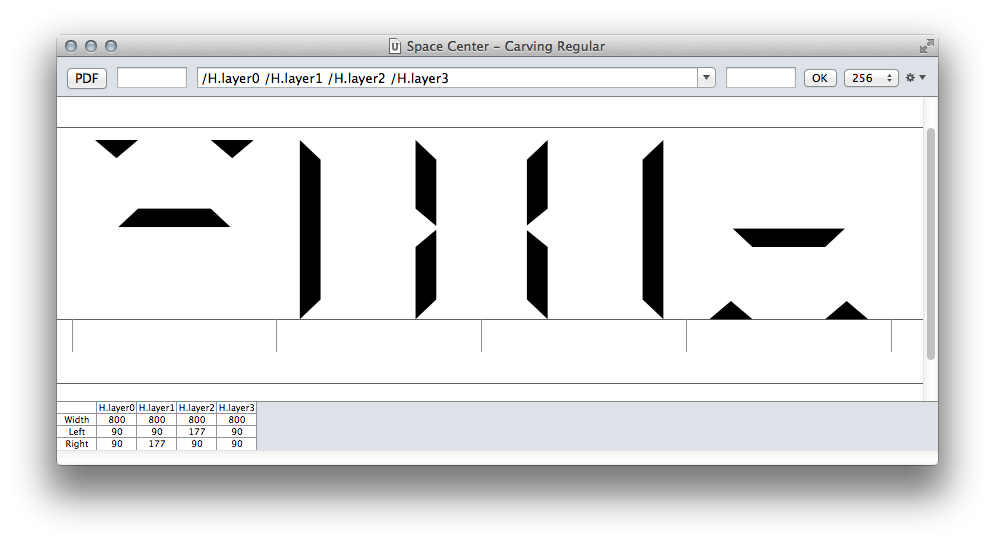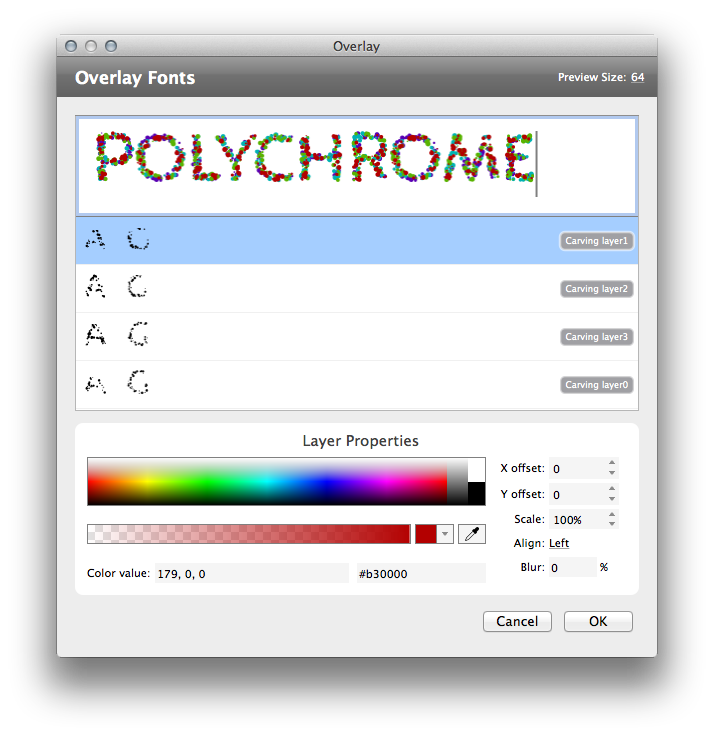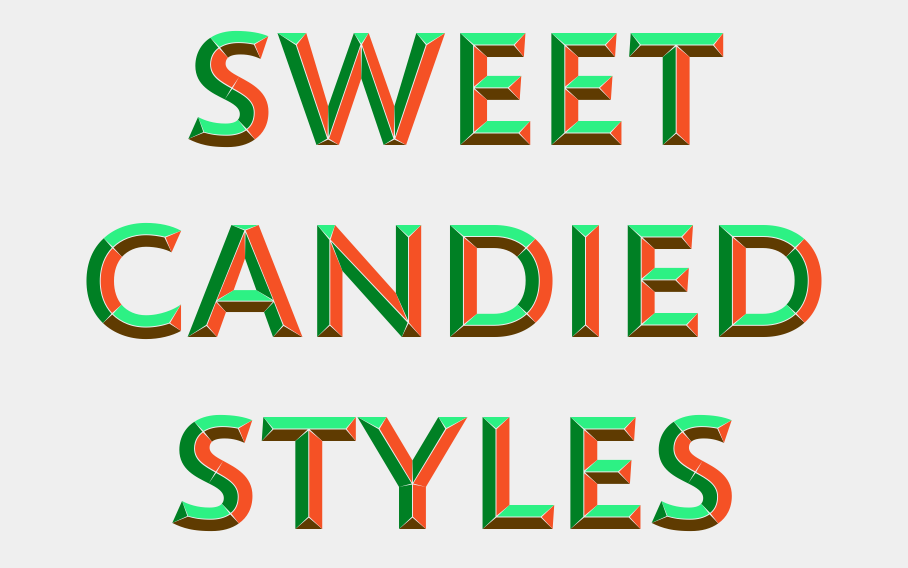
序言
直到最近,在矢量字体的字形中使用多种颜色在技术上是不可能的。要获得多色字母,需要为每种颜色复制内容。就像许多其他技术一样,数字字体需要一段时间才能克服旧技术的限制。当使用木刻或铅字印刷时,每字形只有一种颜色的限制是固有的(除非您计算随机的渐变)。每字形多种颜色需要不同的字体来处理不同的彩色部分,并且每次颜色都需要重新印刷。这已经完美地实现了,一些壮丽的例子图片可以在网上找到。使用叠印,可以仅用两种颜色实现三种颜色的效果。
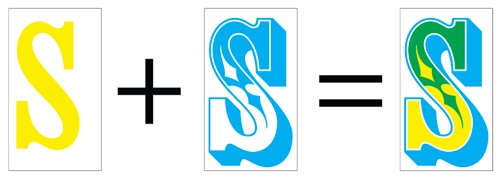
数字字体格式保留了每字形只有一个“表面”的限制。字形中可以有多个轮廓,但是当字体用于排版时,指定的颜色将应用于所有轮廓。类似于凸版印刷,内容需要加倍并叠加才能在每个字形中拥有多种颜色。复制听起来并不是一个优雅的解决方案,而且它是一个持续的错误来源。
直到出现一些表情符号,对多色字体的需求才足够大,足以开发额外的表格来将这些信息存储在 OpenType 字体中。截至目前,有几种不同的方法来实现这一点。Adam Twardoch 在 FontLab 博客上详细比较了所有提议的解决方案。
对我来说,Adobe/Mozilla 的方式看起来最吸引人。
在提出该方案后,它被 W3C 社区小组 讨论并发布为 稳定文档。基本思想是在 OpenType 字体中将彩色字形存储为 SVG。当然,这取决于字体的复杂程度,但 SVG 通常比 PNG 产生更小的文件大小。随着高分辨率屏幕的发展,矢量似乎也比像素更好的解决方案。对 SVG 进行动画处理的可能性是一个有趣的补充,并且肯定会在有趣(和非常烦人)的方式中使用。闪闪发光。
技术
我不是字体技术人员或 Web 开发人员,我只是对这些新发展非常好奇。可能还有其他方法,但这是我成功构建彩色 OpenType 字体的方法。
要制作自己的字体,您需要一个字体编辑器。有几种选择,例如 RoboFont 和 Glyphs(仅限 Mac),FontLab 以及免费的 FontForge。RoboFont 是我选择的编辑器,因为它高度可定制,您可以使用 Python 构建自己的扩展。在一个新字体中,我添加了与最终字体中需要的颜色数量一样多的新图层。您可以立即在不同的图层中绘制,也可以在将轮廓绘制到前景图层后,将它们复制到相应的图层中。使用非常方便的 图层预览 扩展,您可以预览所有重叠的图层。您也可以只增加字体窗口中缩略图的大小。在某个时候,它们将显示所有图层。在检查器中根据您的喜好调整颜色,因为它们用于预览。
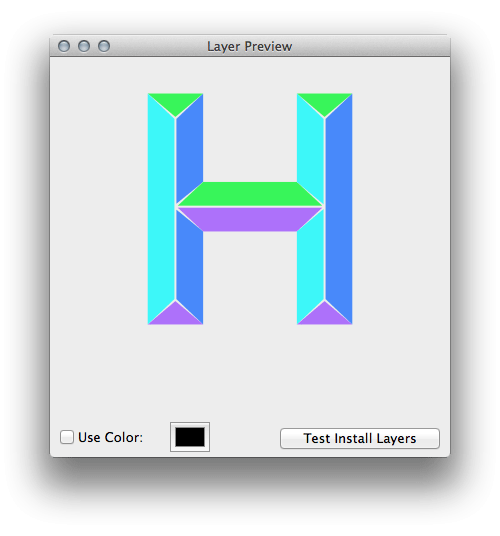
绘制完轮廓后,您需要为每个图层/颜色保存一个 ufo。我使用了一个小 Python 脚本来将它们保存在与主文件相同的位置。
一旦我拥有了所有单独的 ufo,我就将它们加载到 TransType(来自 FontLab)中。只需将您的 ufo 拖放到主窗口中,然后选择您要合并的 ufo。在“效果”菜单中单击“叠加字体…”。您将获得一个预览窗口,您可以在其中为每个 ufo 分配一个 rgba 值,然后单击确定。选择集合中的新添加的字体,并将其导出为 OpenType (ttf)。您将获得一个包含所有 colorfont 版本的文件夹。
RoboChrome
如果您不想使用 TransType,您可能需要看看 Jens Kutílek 的名为 RoboChrome 的功能强大的 RoboFont 扩展。您将需要为每种颜色准备一个单独的基础字形版本,如果您将所有轮廓都放在图层中,也可以使用脚本完成此操作。
Fonttools
您还可以修改已编译字体的 svg 表格,或者如果它还没有,则插入自己的表格。为此,我使用了 Just van Rossum 的非常有用的 fonttools。只需使用您选择的字体编辑器生成一个 otf 或 ttf。打开终端,如果使用 Mac OS 并且安装了 fonttools,请键入 ttx。将字体文件拖放到终端窗口中,然后按回车键。Fonttools 将将您的字体转换为相同文件夹中的 xml (YourFontName.ttx)。然后可以打开、修改和重新编译此文件以生成 otf 或 ttf。
这对于简化程序编译的 svg 并因此减小文件大小非常有用。我重写了一个 1.6mb 字体的 svg,使其降至 980kb。将其用作 web 字体,这会产生很大的差异。如果您要添加自己的 svg 表格和还没有任何表格的字体,您可能需要阅读一些有关所需标题信息的知识。要为要提供 svg 数据的字形提供 endGlyphID 和 startGlyphID,可以在 <GlyphOrder> 表格中找到。
需要注意的一点是两种不同的坐标系。与数字字体相反,svg 具有 y 向下的轴。因此,您要么必须在负空间中绘制,要么反向绘制,然后使用以下命令镜像所有内容
动画
现在,如果您真的想炫耀您的字体,您应该添加一些不必要的动画来惹恼每个人。只需将其插入您想要修改的任何内容的开始和结束标签之间。这是一个示例,它显示了一个圆圈在 500 毫秒内循环地从 0% 到 100% 更改其填充不透明度的示例。
实施
从技术上讲,这些字体应该可以在任何使用 otf 或 ttf 的应用程序中使用。但是,截至目前,只有 Firefox 显示了 svg。如果渲染不受支持,应用程序将只使用常规字形轮廓作为后备。因此,如果您已经准备好了您的字体,那么该编写一些 css 和 html 来在网站上测试和显示它们了。
基本 css
HTML
限制
截至目前(2014 年 10 月),该格式仅受 Firefox (26+) 支持。由于这是由 Adobe 和 Mozilla 发起的,因此将来可能会有更广泛的支持。
虽然使用 svg 具有文件大小合理的优点,并且不需要复制内容,但它也带来一个主要缺点。由于颜色是“硬编码”到字体中的,因此无法使用 css 访问它们。希望这可能会随着 <COLR/CPAL> 表格的实现而改变。
有一个 错误,它阻止 Firefox 32 中播放动画。虽然动画在当前版本 (33) 中呈现,但这可能会由于明显的原因而改变。
根据您建立 svg 表格的方式,它可能会爆炸并导致相当大的文件。如果您使用它们来渲染网站上最关键的内容,请注意这一点。
示例